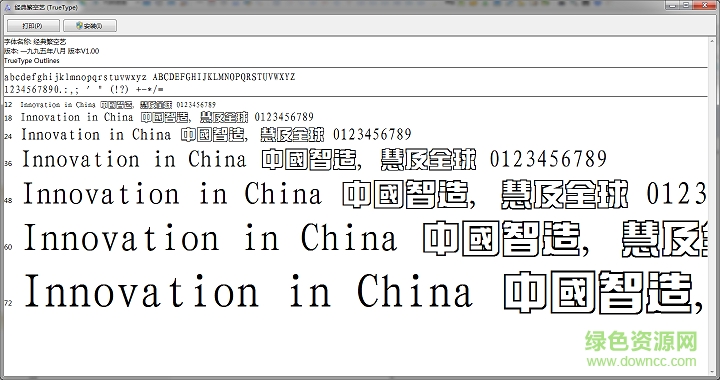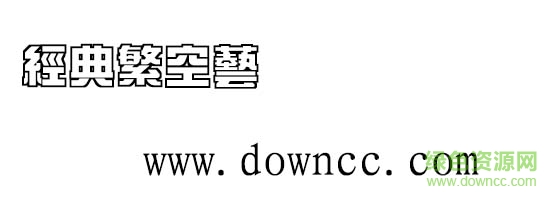
經(jīng)典繁空藝體是一款空心的中文藝術(shù)繁體字體。很多朋友在找經(jīng)典繁空藝簡(jiǎn)體,小編告訴大家,是沒(méi)有的,經(jīng)典繁空藝默認(rèn)是繁體,大家不要浪費(fèi)時(shí)間去尋找了。趕快來(lái)綠色資源網(wǎng)下載吧!
1.中國(guó)的字體設(shè)計(jì)是在印刷術(shù)的產(chǎn)生和發(fā)展中應(yīng)運(yùn)而生的。在古代,中國(guó)的字體設(shè)計(jì)曾有過(guò)輝煌的歷史時(shí)期,在宋朝時(shí)進(jìn)入黃金時(shí)代。
2.清朝末年,鉛字排版印刷術(shù)傳入中國(guó),字體設(shè)計(jì)進(jìn)入鉛字時(shí)代。這個(gè)時(shí)期的字體設(shè)計(jì)既要帶有傳統(tǒng)文化的審美慣性,又要符合鉛字印刷的工藝要求,字體設(shè)計(jì)走到了轉(zhuǎn)折的關(guān)口。
3.鉛字印刷是印刷走入機(jī)械化、工業(yè)化時(shí)代的標(biāo)志,但在這一時(shí)代里,印刷字體設(shè)計(jì)卻始終無(wú)法超越手工勞動(dòng)的制約,無(wú)法擺脫刻模、鑄字、撿字、排版等一系列印前繁雜工藝的束縛